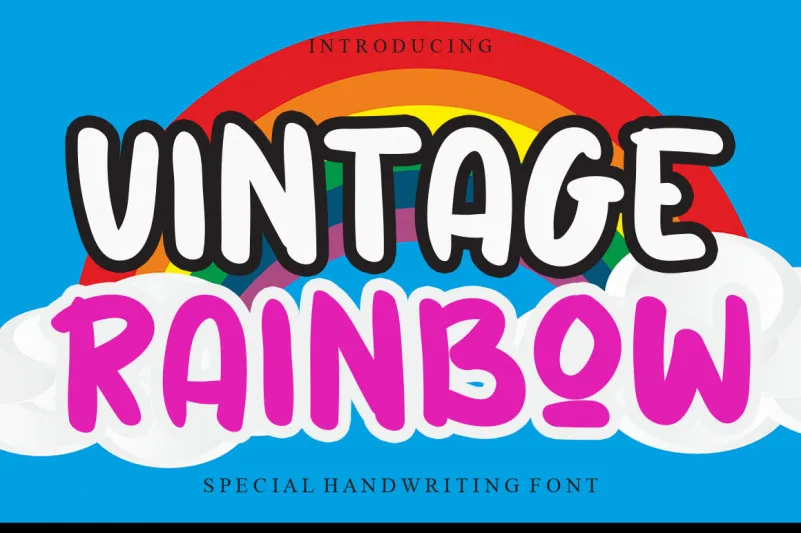
Vintage Rainbow Font – Fonte Grátis
Vintage Rainbow Font
Esta é uma linda fonte para uso em aplicações visuais descompromissadas. Ela se destaca como uma fonte levemente gordinha e colorida, perfeita tanto para design infantil quanto para festas de bebês ou projetos educacionais para crianças pequenas. Seu toque alegre e encantador fará qualquer projeto ganhar um charme único e jovial, tornando-a uma escolha ideal tanto para designers buscando algo divertido e lúdico como para aqueles que desejam adicionar um toque infantil em seus trabalhos. Perfecta para crianças, esta fonte tem o potencial de fazer qualquer design ganhar vida e ser capaz de cativar os mais jovens ou tornar qualquer projeto ainda mais encantador para a infância.